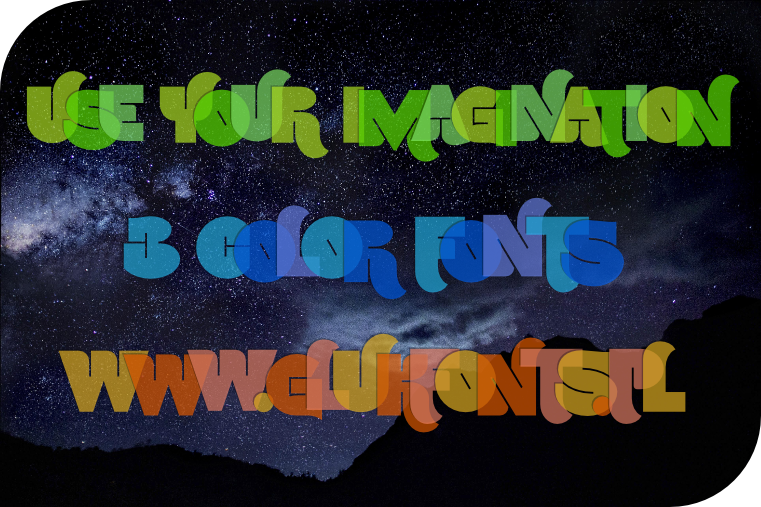
Fonty UseYourImaginationR, G i Bsą kolorowymi fontami z wpisanymi na stałe wartościami kolorów w nowym formacie. OpenType SVG font jest propozycją wielokolorowego, wektorowego formatu fontów i został zaimplementowany w Mozilla Firefox (v. >= 26), Microsoft Edge (v. >= 38.14393), Adobe Illustrator CC 2018 i Adobe Photoshop CC 2017.